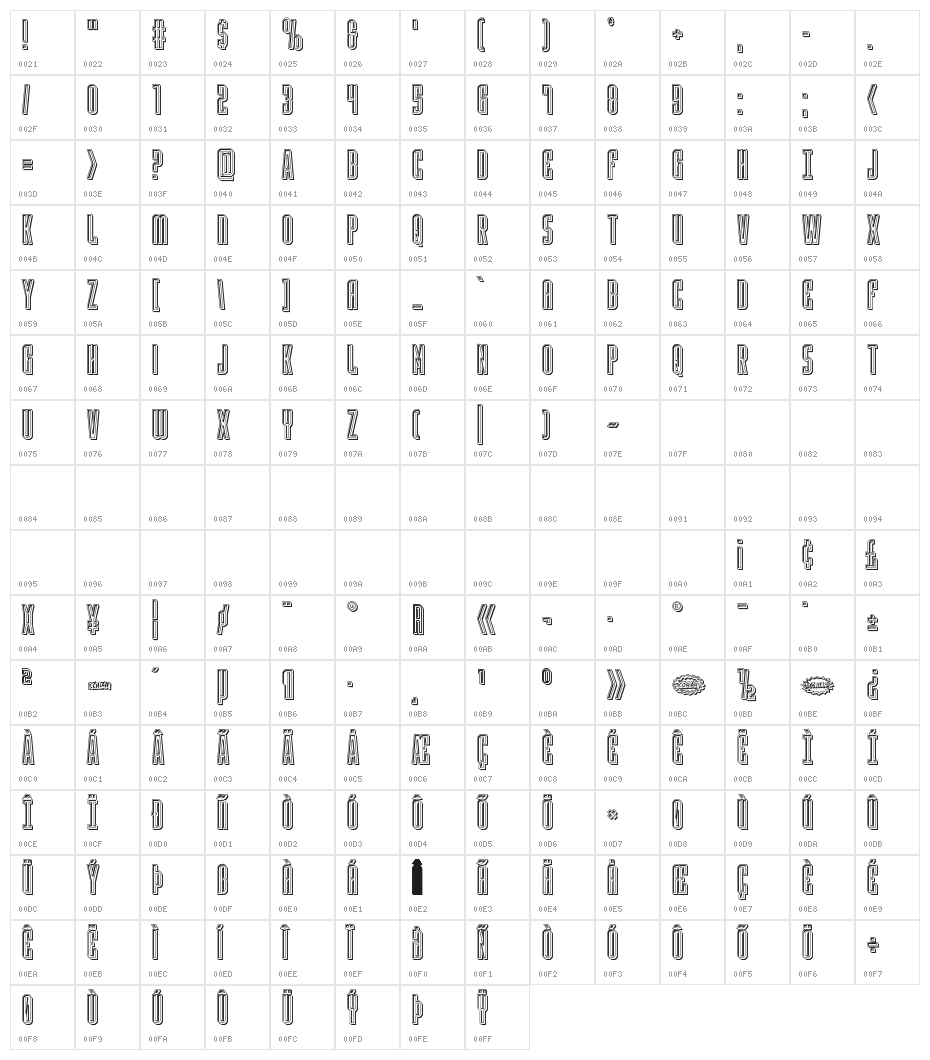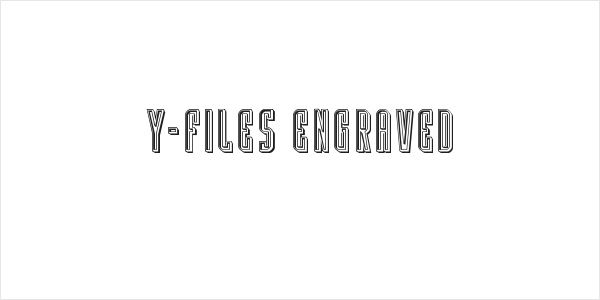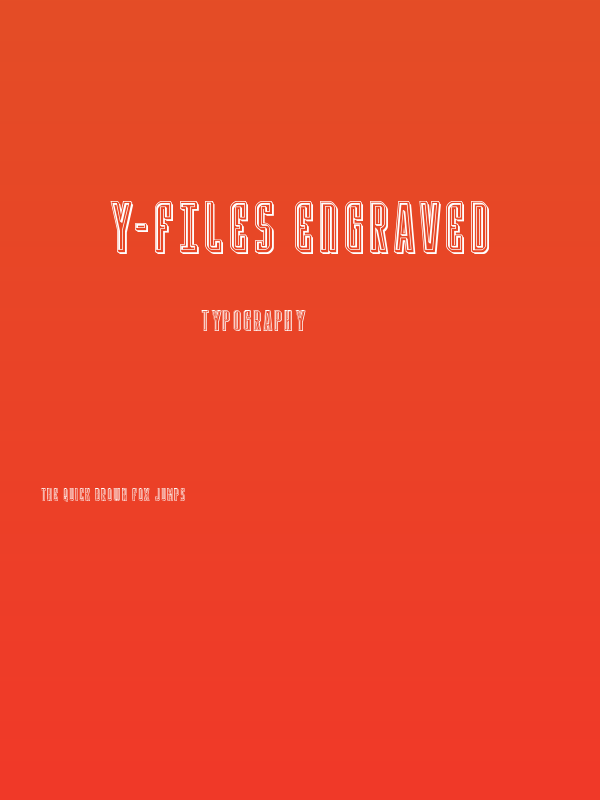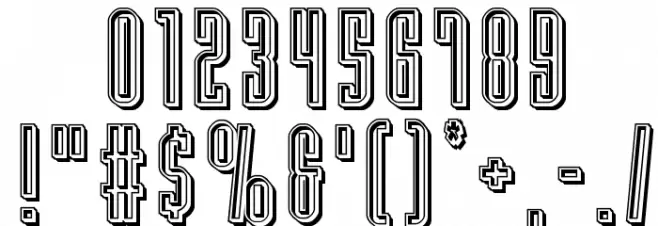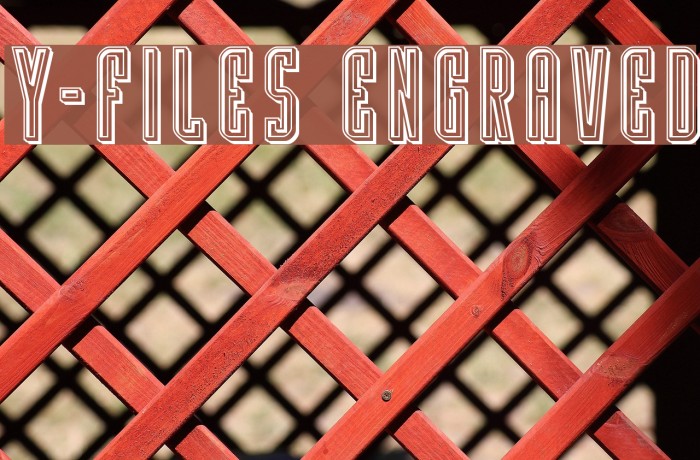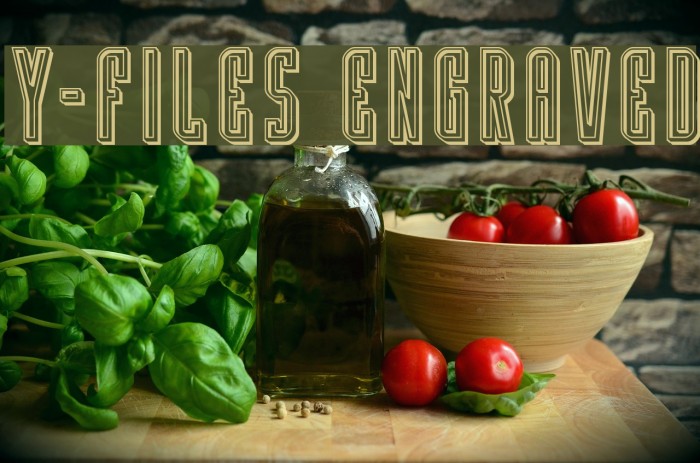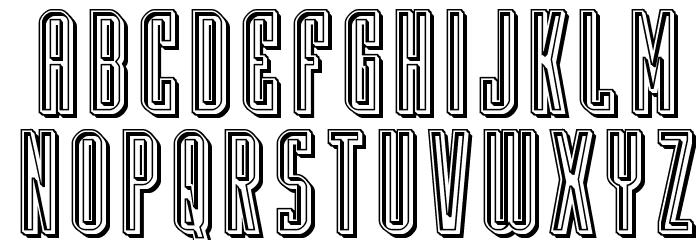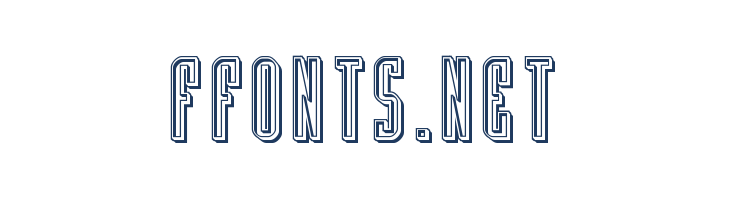
Y-Files Engraved Font
| Общий стиль | Vintage |
| Рекомендуемые проекты | Ideal for use in vintage-themed designs, signage, posters, and branding projects that require a touch of elegance and sophistication. |